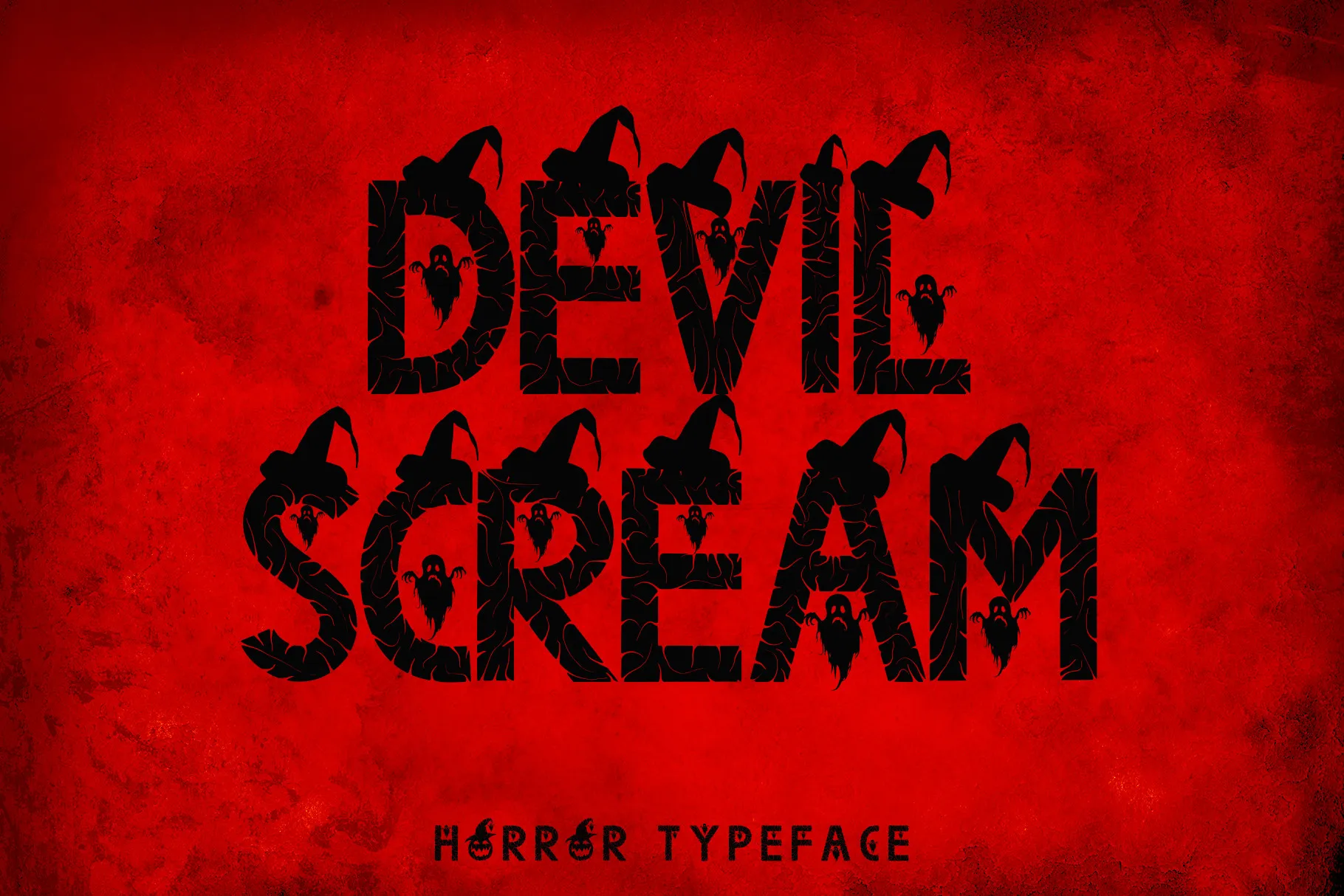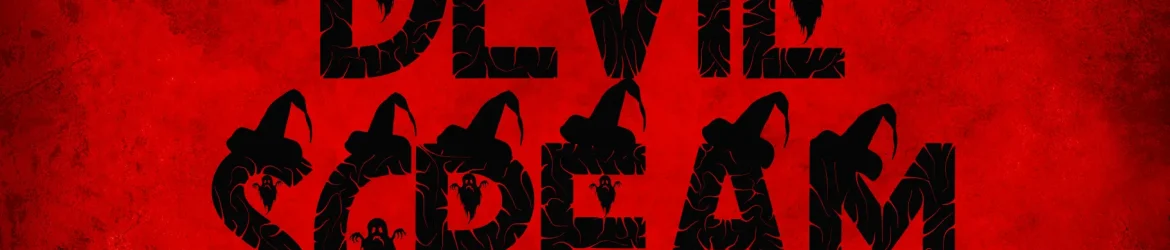
Essa é uma fonte deslumbrante e assustadora, perfeita para qualquer projeto que exija uma pitada de espírito malévolo. Através dessa fonte, você pode transformar qualquer texto em algo extraordinariamente atrativo e dramático. Seja em um site de notícias, um livro infantil ou até mesmo em uma capa de revista, o resultado é garantidamente inesperado e impressionante. Desenvolvida pela Yoga Letter, a fonte ‘Devil Scream’ pode ser usada para qualquer tema, seja ele educativo, informativo ou simplesmente divertido. O design tem a capacidade de dar um toque único e assustador a qualquer trabalho de design. Não importa se você está criando uma identidade visual para um negócio, produzindo materiais publicitários ou mesmo desenhando algo artesanal em casa – essa fonte é certamente uma ferramenta indispensável para quem busca dar personalidade à sua marca. Sua versão Display oferece a liberdade de transformar qualquer projeto em uma experiência visual realmente memorável e inovadora.